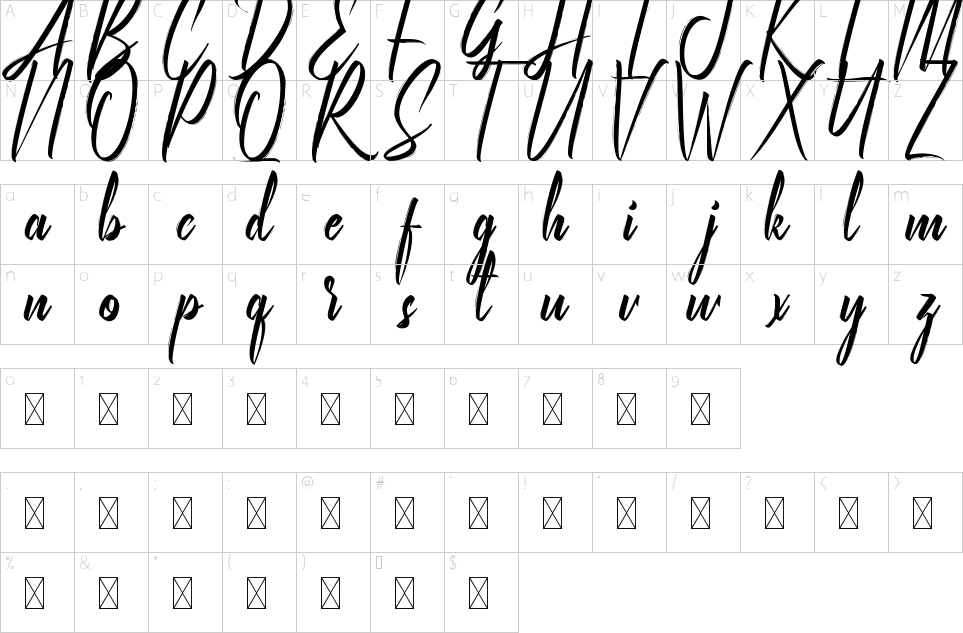
Glossariest Font
Descubra a beleza elegante da Glossariest Font para Windows e Mac. Esta fonte foi projetada pela equipe RaisProject e tem sido baixada por 2,451 usuários. Sua tipografia clássica e sofisticada é perfeita para aplicativos de design gráfico ou criação de sites profissionais. Composta em 36 caracteres distintos, a Glossariest oferece uma variedade que vai desde letras minúsculas até símbolos especiais, ideal para personalizar seu projeto de qualquer maneira. Seja você um designer experiente ou iniciante, esta fonte será um elemento incrível em seu próximo projeto. Download da Glossariest Font agora e encontre a perfeição no design.